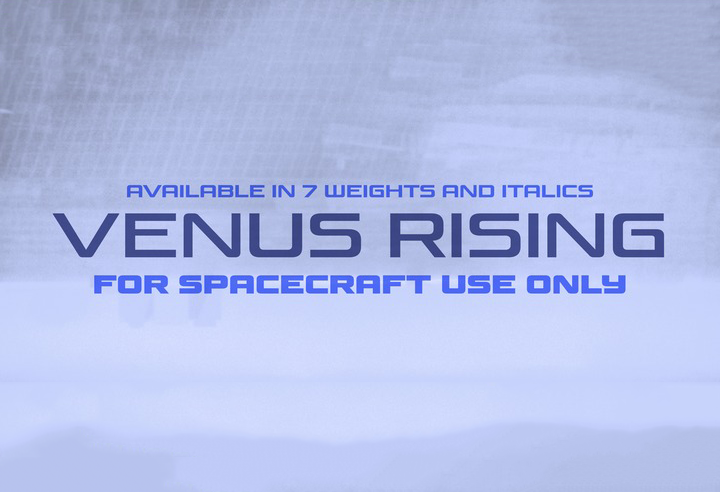
Através do mundo da tipografia, encontramos uma nova descoberta que certamente se encaixa perfeitamente para nossas necessidades digitais: a Venus Rising Font Family. Inspirada na essência de Vênus, esta família de tipo serifless apresenta uma modernidade quase ultramoderna. Os arquitetos da Typodermic criaram um design quadrático e extremamente funcional que está prestes a revolucionar o mundo das escritas digitais. A Venus Rising é mais do que apenas outra fonte. Ela suporta praticamente todos os idiomas latinos, bem como grego e cirílico, tornando-a uma opção versátil para qualquer aplicação ou projeto. Não se contentando apenas com as funções básicas de um tipo serifless, a fonte oferece recursos avançados do OpenType, incluindo ordinais numéricos, frações e alternativas para o Q e Y. Venus Rising é uma fonte perfeita para aquelas aplicações que exigem modernidade e versatilidade. Seja para aplicativos de design gráfico profissional, publicações digitais ou qualquer projeto criativo que precise de uma base visual única e atraente, esta família de tipo certamente será um grande atalho para seus objetivos. Em seu DNA está a essência da modernidade e uma capacidade de se adaptar às diversas necessidades do design digital atual.